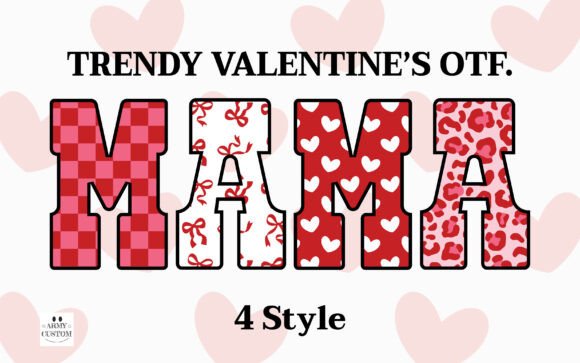
Trendy Valentine's
Если вы ищете высококачественные ресурсы, такие как Trendy Valentine's, этот премиум-пакет — фантастический выбор для ваших творческих проектов.
Созданный с высокой точностью, Trendy Valentine's предоставляет чистые векторы, плавную типографику и коммерческую лицензию для вашего спокойствия.
Создаете ли вы продукты POD (печать по требованию), свадебные приглашения или графику для социальных сетей, Trendy Valentine's станет идеальным выбором.